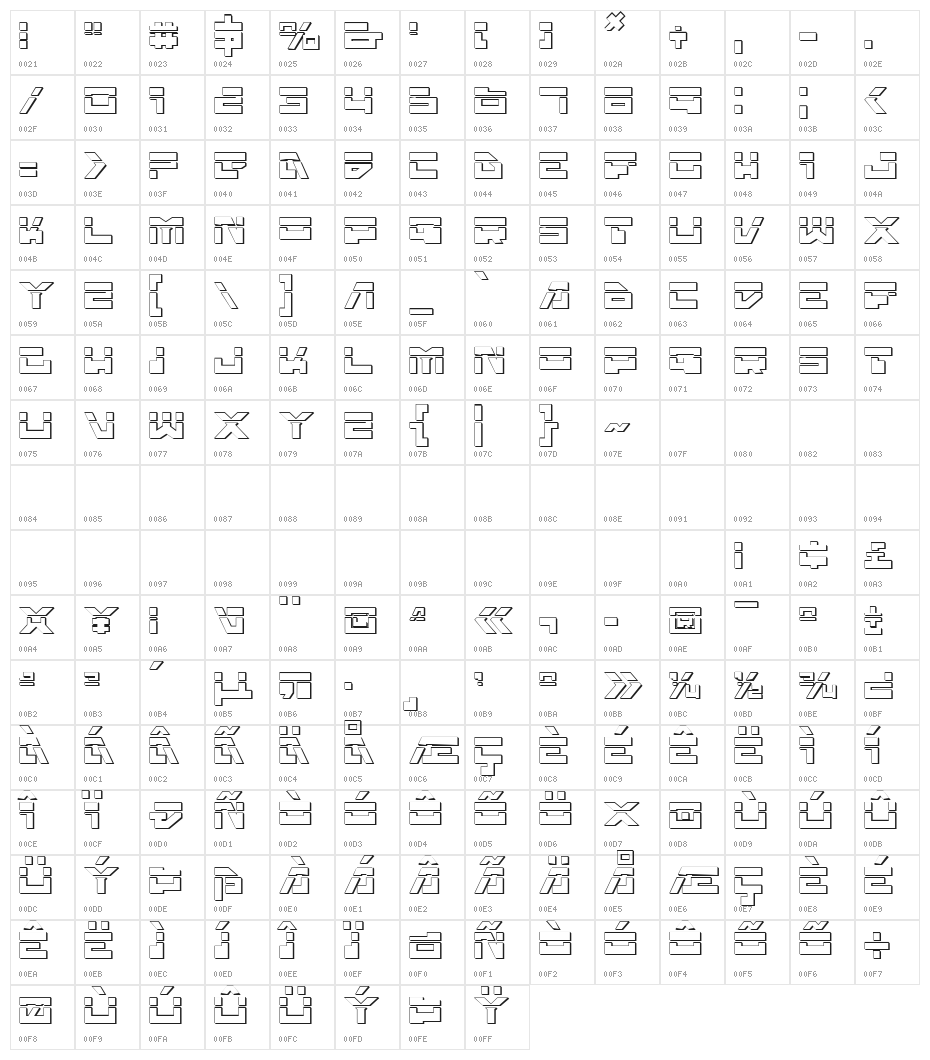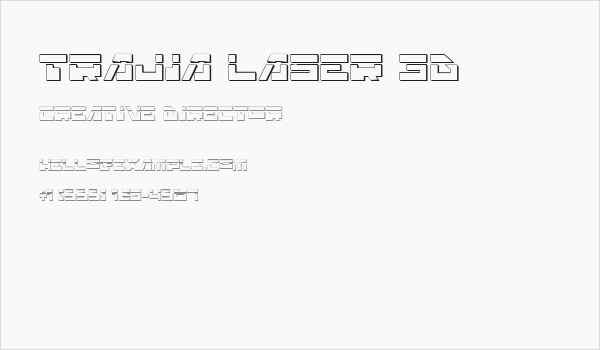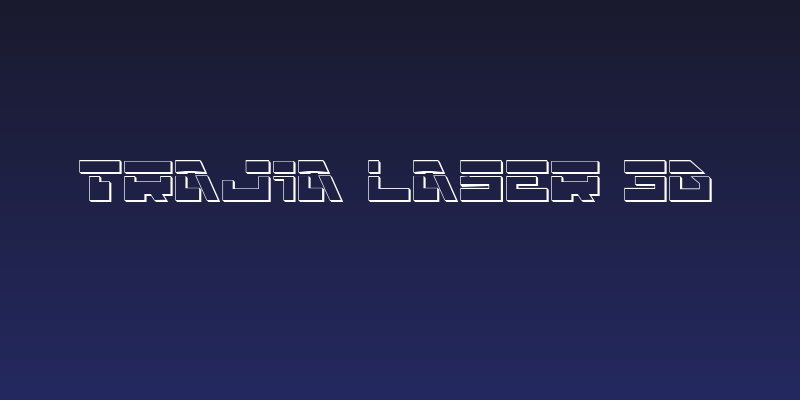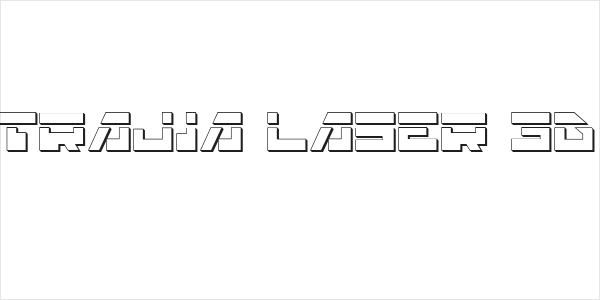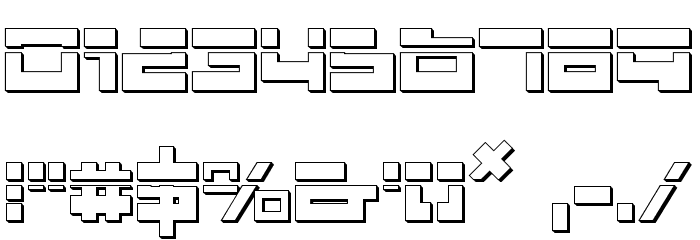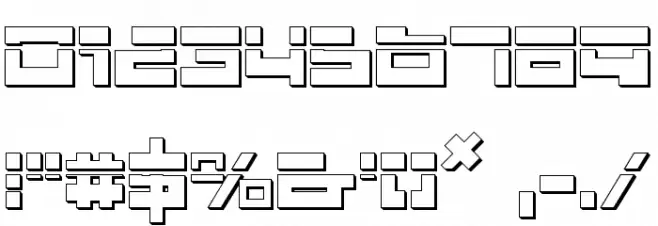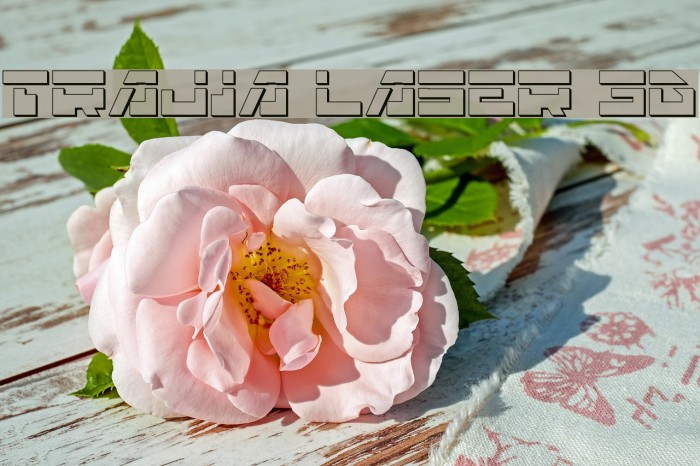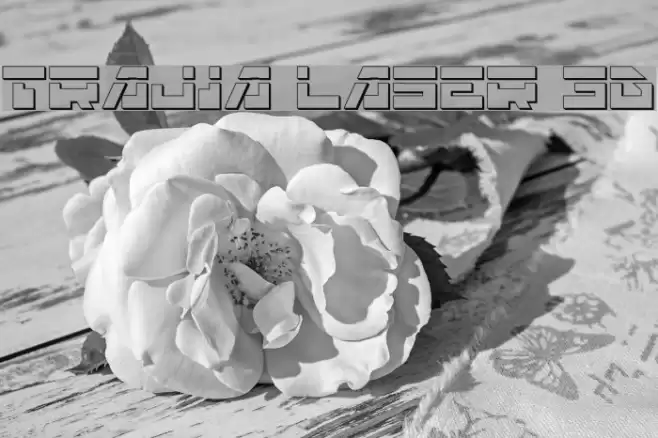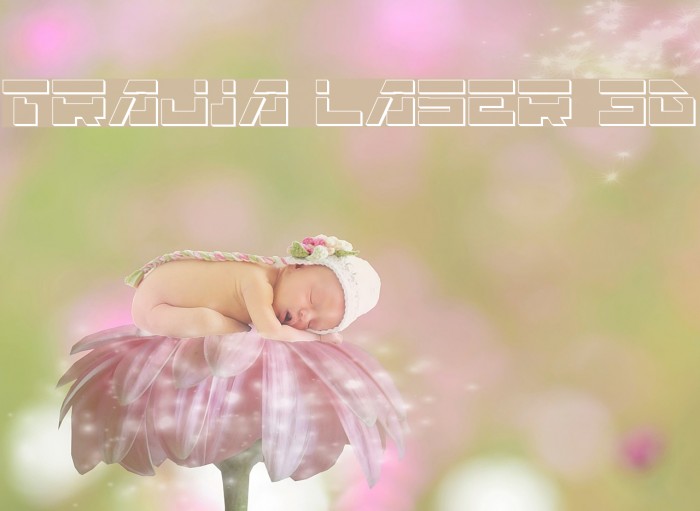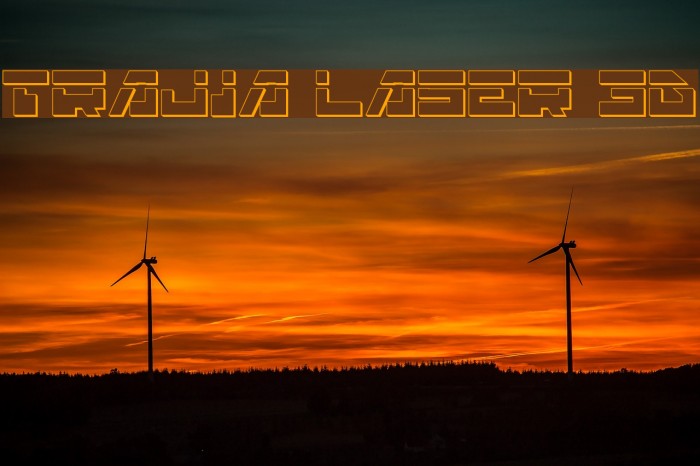
Trajia Laser 3D Font
✎ Sci-fi
| Vorgeschlagene Projekte | Ideal for technology branding, video game titles, sci-fi themed designs, and digital media. |